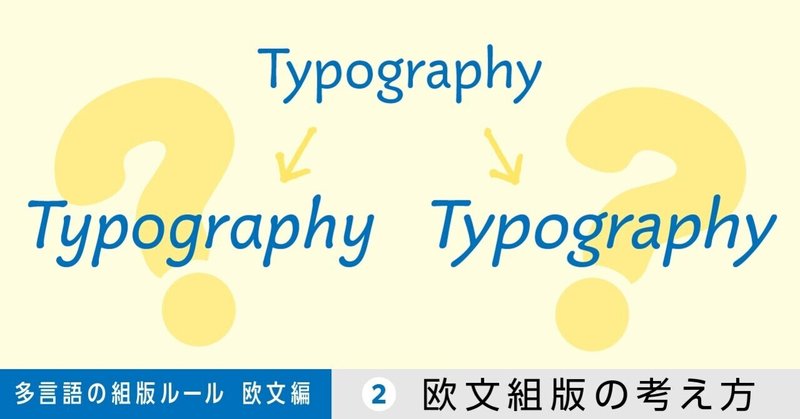
多⾔語の組版ルール【欧⽂編】第2回 欧文組版の考え方
第2回ではさっそく、欧文組版をするにあたって重要となる基本ルールをお伝えします(欧文組版で用いるラテン文字や文字セットについては、「第1回 欧文の基本」で説明しています)。
1. 文字/単語のとらえ方の違い
日本語の和文組版に慣れている方が、欧文組版に取組むときに、念頭に置かなければならないことは、組版のしくみの違いです。
和文組版では、基本的に図1のような四角い仮想ボディを持つ文字を、前に送っていきながら配置していく考え方をしています。
文字単位で揃えていく組版ですので、行末を揃えやすく、多くの場合「箱組み*」が採用されます。和文組版は、「文字」単位で組版を考える仕組みを持っているといえます。
*箱組み
左右版面に均等に流し込み、最終行のみ左揃えになる組み方のこと。
ジャスティファイとも言う。
しかし欧文組版の場合は、和文のように1文字単位で考えることはありません。和文の1文字単位にあたるものは「1単語(ワンワード)」です。
たとえば「I(アイ)」のように1文字であっても、1単語として考える感覚が必要になります。
欧文の各単語間には、1スペースが入ります。
このスペースの間隔はすべて同じになればよいのですが、「箱組み」を採用した場合、図2のように単語の間隔(ワードスペース)が行ごとに違うものになります。
「ラグ組み*」の場合は、ワードスペースは均等になりますが、その行が含む単語の長さに、行末が大きく影響を受けます(図3)。そのため、行末が行によって不揃いになります。
*ラグ組み
テキストを左揃えにし、行末は成り行きで改行される組み方のこと。
アンジャスティファイとも言う。
欧文組版は、行末やワードスペースの不揃いが、読み手の邪魔をしないように整えていく作業ともいえます。
「読み手の邪魔をしない行末」の調整のためには、「ハイフネーション」の設定が重要です。
また、「読み手の邪魔をしないワードスペース」を整えるためには、「ジャスティフィケーション」の設定が重要になります。
この2つの設定は、欧文組版をする上で欠かすことができません。
ハイフネーションとジャスティフィケーションは、3・4章で詳しく説明します。
2. 欧文組版は「段落単位」で考えよう
そして、もうひとつ重要な組版の考え方が「行単位」「段落単位」です。
和文の考え方では、図4のように「行単位」で組版を考えていきます。
これは、欧文組版でも有効ではありますが、欧文組版では、文字ではなくスペース部分を調整していくことが重要ですので、図5のように、「段落単位」で組版を考えると、より調整がしやすく効率的です。
たとえば和文組版では通常、「2行目のワードスペースを整える」ために、1行目のワードスペースをツメて、2行目の先頭の単語を1行目の行末に入れる、ということを行います。
しかし欧文組版の場合、段落全体を見渡し、一番ワードスペースの広いところとせまいところを見つけ、その間の行を少しずつ調整します。「段落全体」の行で助け合い、調整するのです。
このように工夫することで、読者の邪魔にならないワードスペースを作るように努めます。
3.行末調整の「ハイフネーション」
3.1 音節で正しく区切る
欧文組版で、最も重要な作業が「ハイフネーション」の設定です。
ハイフネーションは、行末で単語を分け、2行にまたがって組版することで、日本語では分綴(ぶんてつ)ともいいます。
ハイフネーションを、「どこで切ればよいかわからない」という理由で、「ハイフネーションをしない」という選択をしている欧文組版を、日本ではよく見かけます。
この選択は、欧文組版としては正しい選択とはいえません。ネイティブの人たちから見れば「ハイフネーションをし忘れている」と思われてしまいます。
ハイフネーションは、上図のように音節によって区切られる箇所にのみ入ります。この場所は、一般的な英語辞書などに掲載されています。
また、InDesignなどの組版アプリケーションには、各言語に対応したハイフネーションの辞書が搭載されていますので、正しく設定をして使えば、とても有効的です。
英語では『New Oxford Spelling Dictionary』などハイフネーション専用の辞書も販売されています。これらの辞書では、ハイフネーションの優先順位も表記されています。
3.2 ハイフネーションの設定
ハイフネーションを使用するために、次の7つの設定を最初に決めておくとよいでしょう。
(1)何行まで続けて入れてOKとするか
(2)単語頭/末尾は何文字から入れるか
(3)何文字の単語から入れるか
(4)ラグ組みの場合、行末のどの範囲から入れるか
(5)段落末には入れるか
(6)段間末には入れるか
(7)大文字はじまりの単語には入れるか
(1)何行まで続けて入れてOKとするか
一般的には、3行までが許容範囲とされています。 4行以上も続けて行末にハイフネーションがされていると、だらしのない組版の印象を与えてしまいます。
2行までを基本として、やむを得ない場合に3行まで続けて入れる、という設定を基本に考えるとよいでしょう。
(2)単語頭/末尾は何文字から入れるか
単語頭/末尾ともに2文字目からハイフネーションを入れることが可能な単語であっても、短くこまごまハイフネーションされてしまうケースが増え、読みづらくなります。
前後「3文字から入れる」を基本にして、例外的に2文字を許可する設定にするとよいでしょう。
ただし、スピード感を持って作業を進める必要がある場合や、組幅が狭く単語間隔の調整が難しい場合は、「2文字から入れる」としても問題ありません。
(3)何文字の単語から入れるか
単語を構成する文字数による設定をします。
あまり短い単語はハイフネーションをしないほうが望ましいので、5文字または6文字の単語からハイフネーションさせるとよいでしょう。
(4)ラグ組みの場合、行末のどの範囲から入れるか
ラグ組みの場合、行末の版面から何mmの範囲でハイフネーションを許可させるか、という目安をつけておくと、行末の不揃いをほどよくさせることができます。
(5)段落末には入れるか
(6)段間末には入れるか
(7)大文字はじまりの単語には入れるか
上記3つについては、基本的には入れないようにするとよいですが、欧文組版はその行の単語の長さに左右されますので、場合によっては、ハイフネーションせざるを得ない場合があります。
(5)(6)については、ワードスペースまたは行末のアキ具合とのバランスをみながら、適宜判断をしましょう。
(7)については、固有名詞の場合は初出のハイフネーションを避け、2回目以降は、ハイフネーションを許可するというルール設定などが考えられます。
なお、固有名詞のハイフネーションには、注意が必要です。特に日本語の固有名詞の場合は、正しい母音で区切れていることを必ず確認しましょう。
また、「Japanese」という単語には要注意です。
「Jap-」でのハイフネーションは、辞書では正しい位置ですが、「Jap」という言葉は差別用語ですので、ここでのハイフネーションは避けましょう。
辞書を確認せずに「Japan-ese」とハイフネーションしている例も時々見かけますが、これは間違いです。「Japa-nese」でのハイフネーションを心がけましょう。
欧文組版では、組版が終わったあとには必ず「行末の確認」をします。これは、ハイフネーションに問題がないかを確認するためです。
この「行末の確認」はとても大切な作業です。きれいな組版の実現のために、習慣づけるようにしましょう。
4. ワードスペースを調整する「ジャスティフィケーション」
「箱組み(ジャスティファイ)」で欧文組版をする場合には、必ず「ジャスティフィケーション」を設定します。これは、QuarkXpressやInDesignなどの組版アプリケーションには必ず搭載されている重要な機能です。
余白や文字サイズなどにより、フォントが持つ本来のスペーシングでは、文字と文字の間隔(レタースペース)や、ワードスペースのバランスが悪い場合があります。ジャスティフィケーション設定を使い、ちょうどよいスペーシングに設定することが大切です。
調整は、段落最後の「ジャスティファイされていない行」を目安にしながら、そのワードスペースと、ジャスティファイされている行とのワードスペースのバランスを見て調整していきます。
5. イタリックの使用方法
欧文組版の本文組みでは、必ずといってよいほどイタリックを使用します。そのため、本文向けに開発された欧文書体には基本的にイタリック体が用意されています。和⽂組版で使う書体には「ひらがな」「カタカナ」がいつも揃っているように、欧⽂組版の本⽂組みでは「ローマン体(アップライト)」「イタリック体」が切り離せません。
イタリックを使う場面
強調、 CDアルバムタイトル(曲名はローマン体で引用符で囲う)、美術などの作品名、映画タイトル、書籍名、雑誌名、新聞名、外国語、小説などの過去の回想シーンや手紙の内容などの表記
Adobe InDesignの歪み機能やIllustratorのシアー機能を使い、ローマン体を斜体にすることもできますが、イタリック体の代用にすることはやめましょう。
イタリック体<画像上>と、シアー機能により斜体(擬似的イタリック)にしたローマン体<画像下>では、同じ書体でもまったく異なることがわかります。 英語が母国語の国から発信される欧文組版において、特に書籍組版では、擬似的イタリックが使われることはありません。
フォントとしてあらかじめデザインされたイタリック体は、ローマン体に比べて、タイトなスペーシングや手書きの風合いのある字形が採用されていることがあります。これらによって文中のローマン体との区別が明確になります。
欧文組版の本文組みでは必ず、イタリック体があるフォントを選び、活用しましょう。
今後も、和文と異なる、欧文組版ならではの考えかたを説明していきます。言語によって、組版ルールをきちんと切り替えましょう。